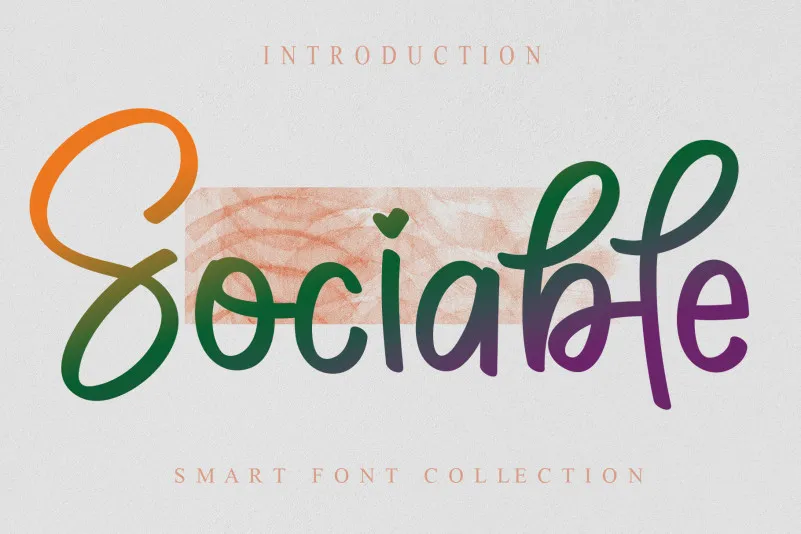
Sociable Brush Font – Fonte Grátis
Sociable Brush Font
A Sociable Brush Font é uma elegante escolha para quem busca personalidade em cada letra. Criada pelo talentoso designer creativeletter, esta fonte script oferece uma experiência única e divertida de escrita. Suas linhas suaves e curvas leves criam um tom descontraído que não só ilumina qualquer texto, mas também reflete a essência vibrante do idioma português brasileiro. Perfeita para designers que valorizam a personalização e o toque humano em seus projetos digitais, Sociable Brush é uma escolha brilhante tanto para aplicativos de redes sociais quanto para criações gráficas com um tom descontraído. Nossa fonte é perfeita para quem deseja dar vida à sua ideia e transformá-la em algo único e envolvente, seja ela um blog, uma arte digital ou qualquer outro projeto que você possa imaginar.